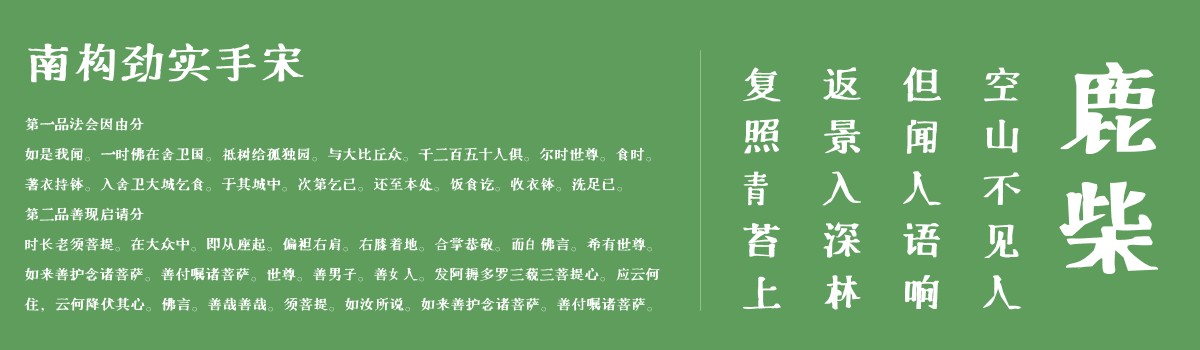
南构劲实手宋
这款南构劲实手书字体跟这个名字一样,非常的与众不同,笔画中运用大胆的设计,若虚若实,奇险而卓绝的笔画体现,是现代字体的一种表达方式,这款字体非常适用于个性的广告设计,标题应用,产品包装以及其他一切需要用吸引眼球的字体载体上,现在字体家网站已经开放个人版下载和正版在线购买,欢迎体验,购买正版字体,就上字体家!